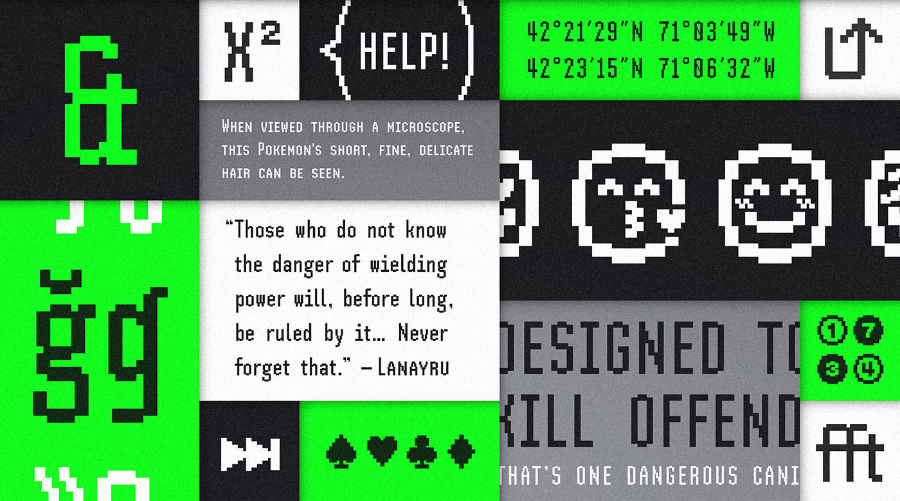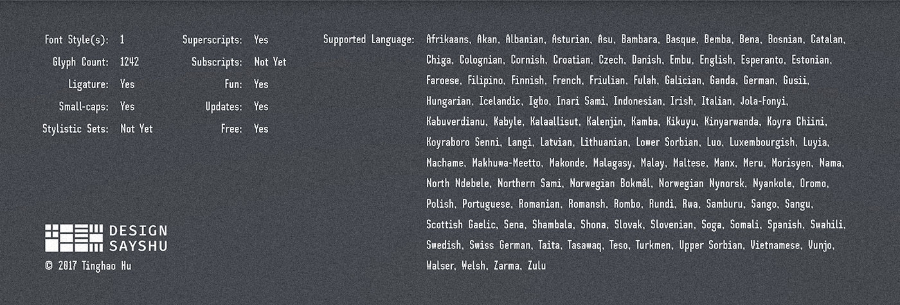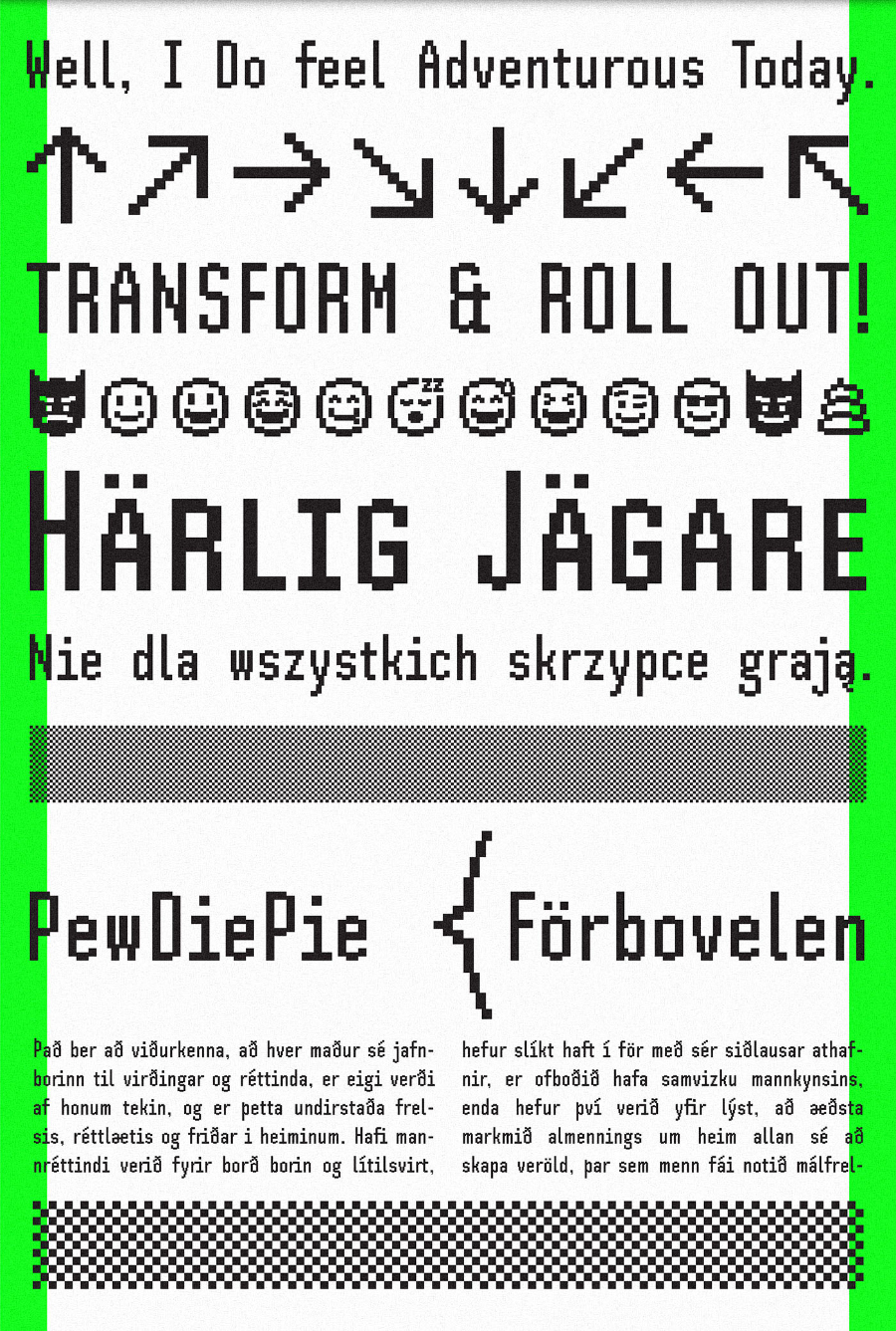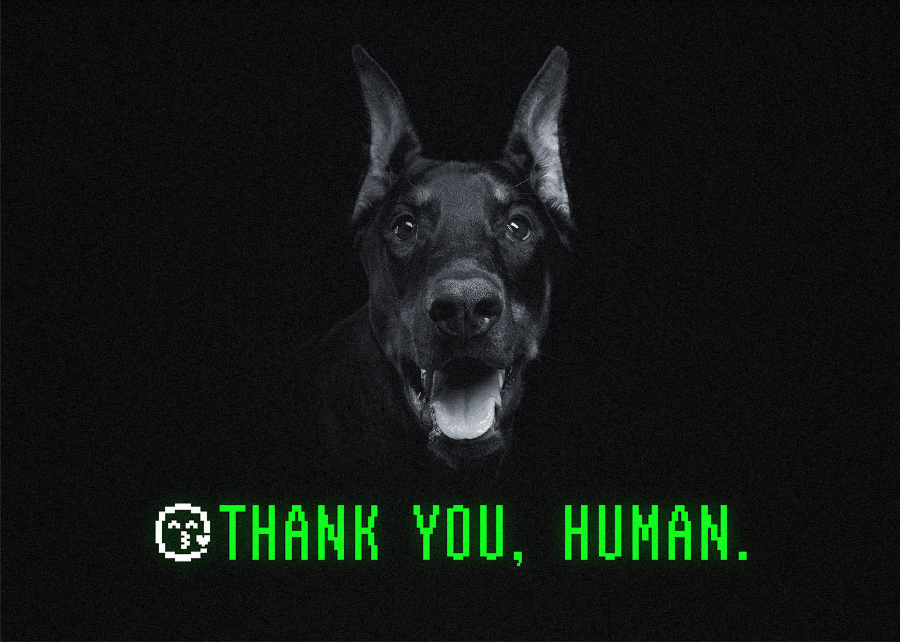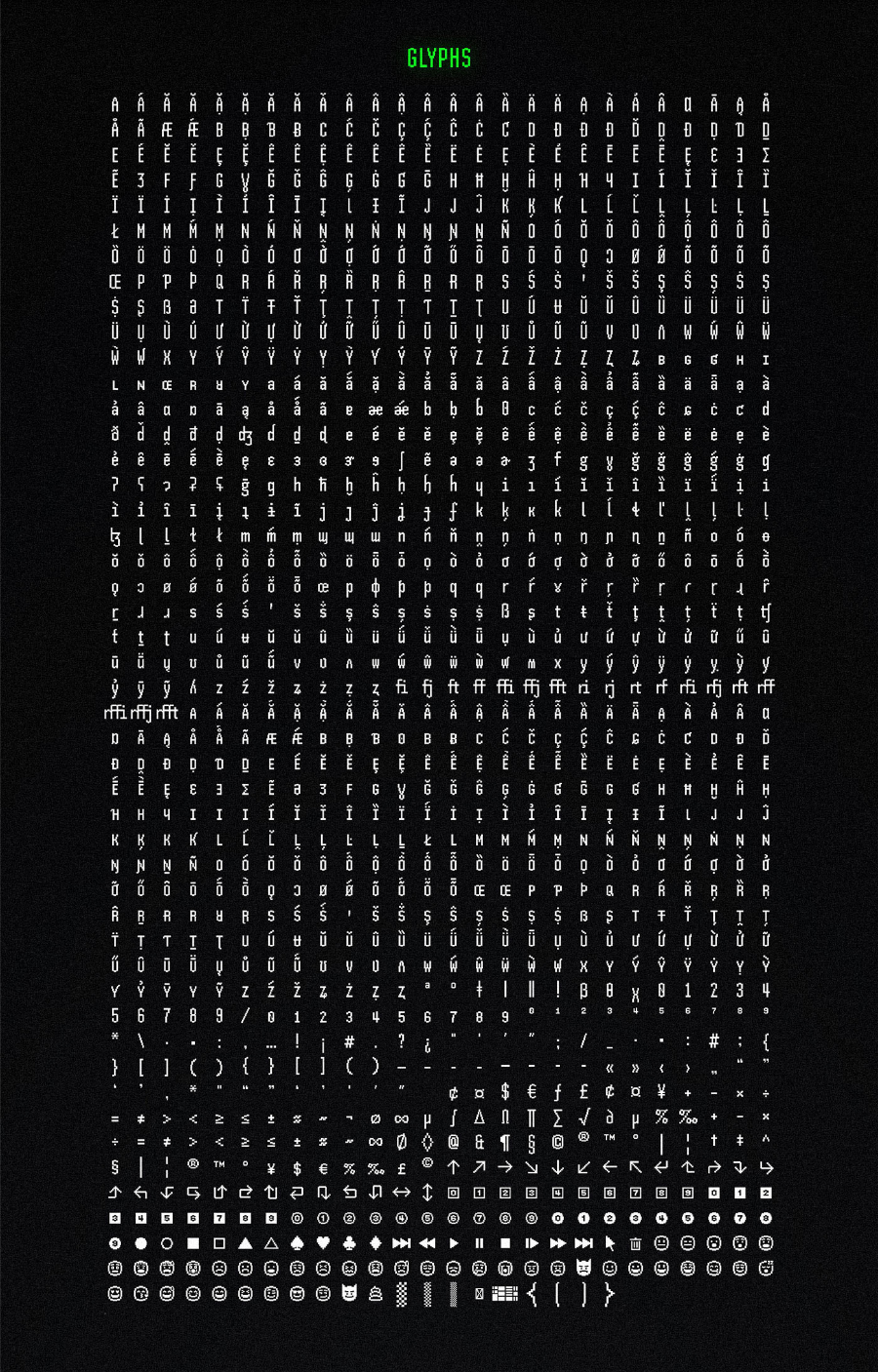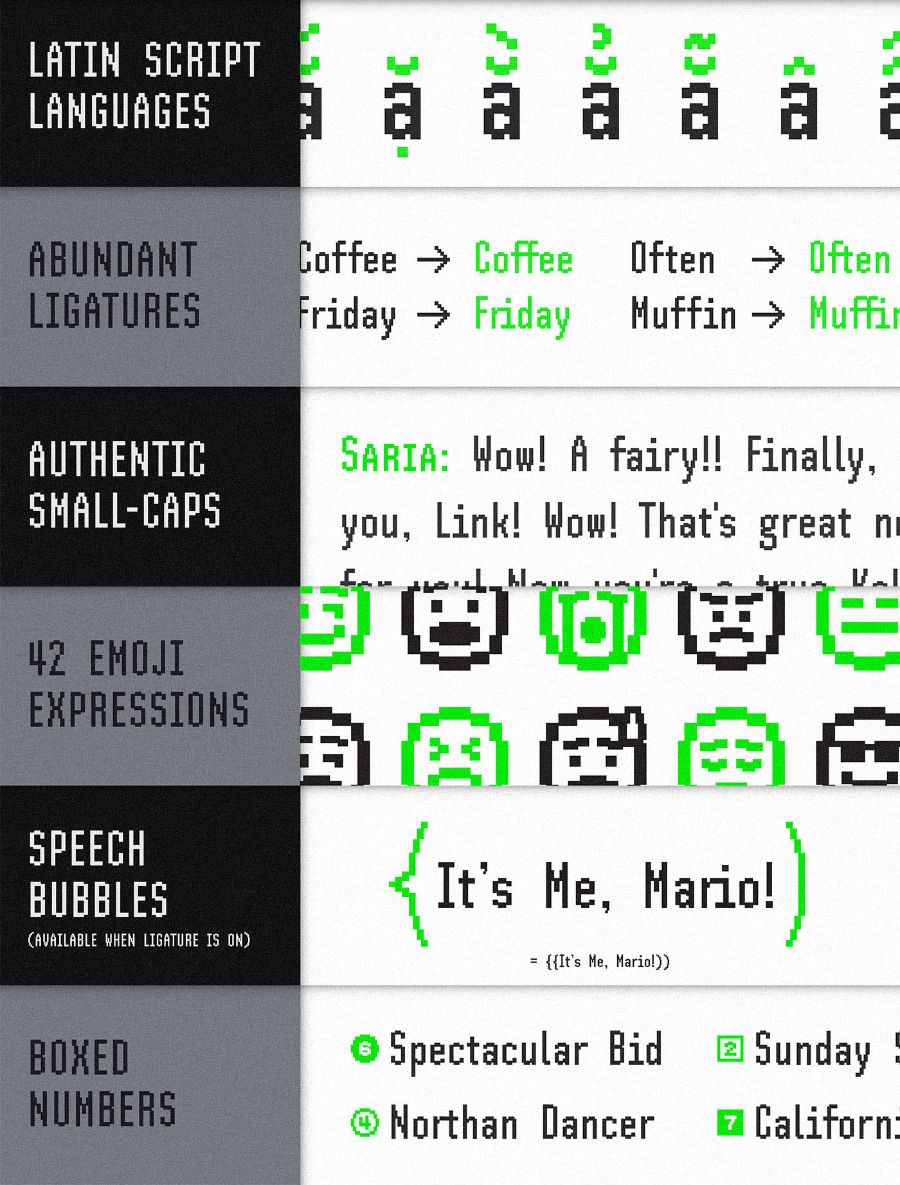
Pinscher免费位图字体
这里来Pinscher免费位图字体!就像杜宾犬一样,SH Pinscher很苗条,优雅,专注,乐趣,并且设计成同时杀死所有人。这个野兽比野外的典型的位图字体更具印刷性,它带有连字,小写字母,符号,支持的语言,甚至表情符号。好的,所以你已经抓住了SH Pinscher作弊的细节,以获得比“真实”的位图字体更好的可读性和可读性。